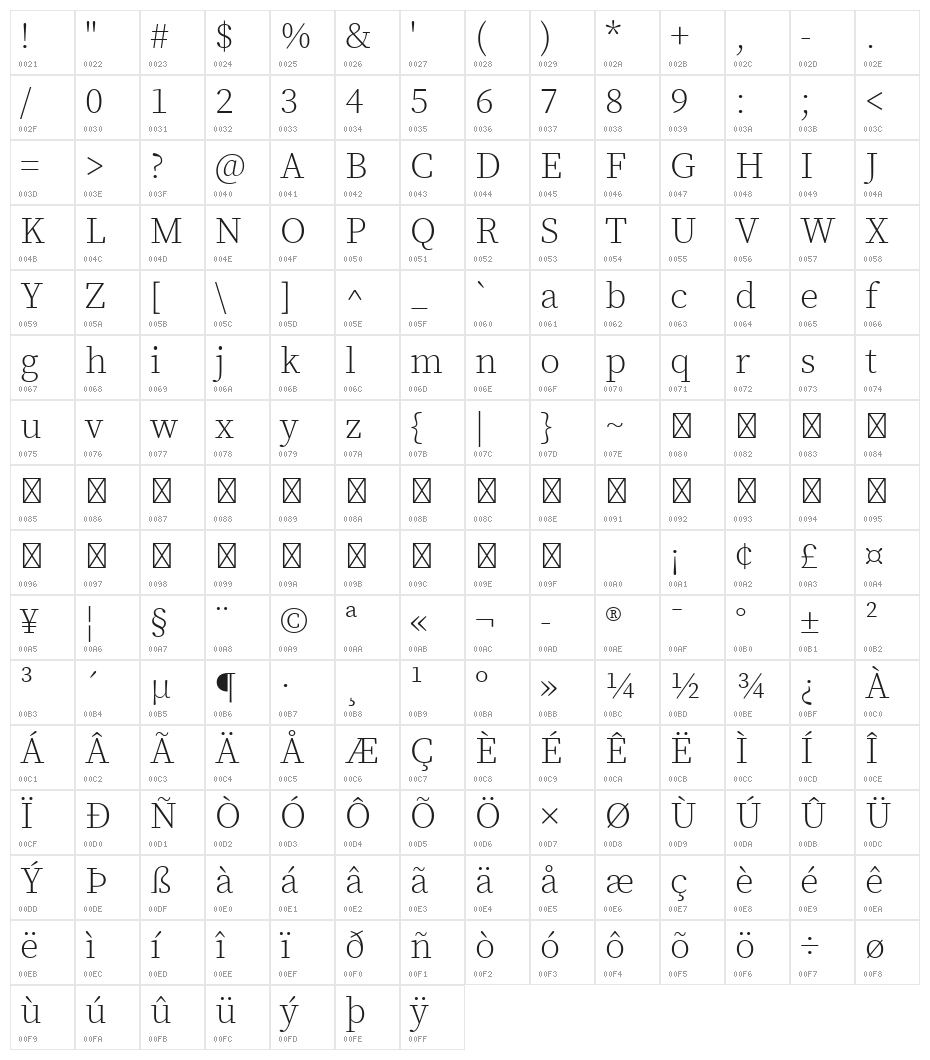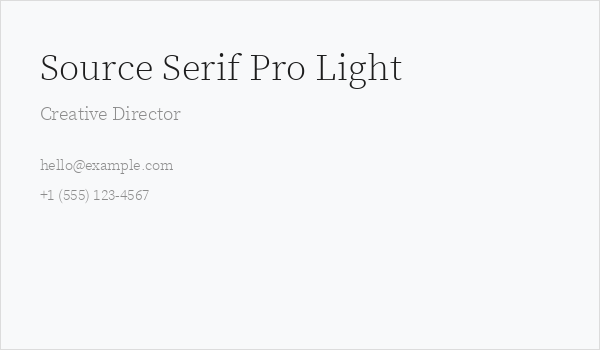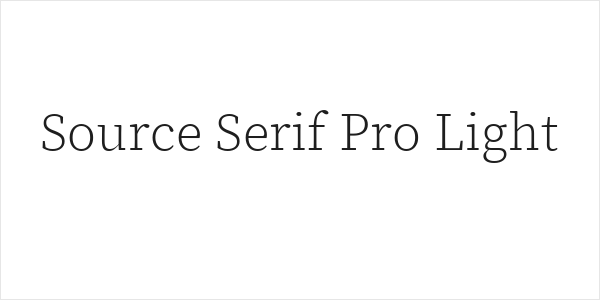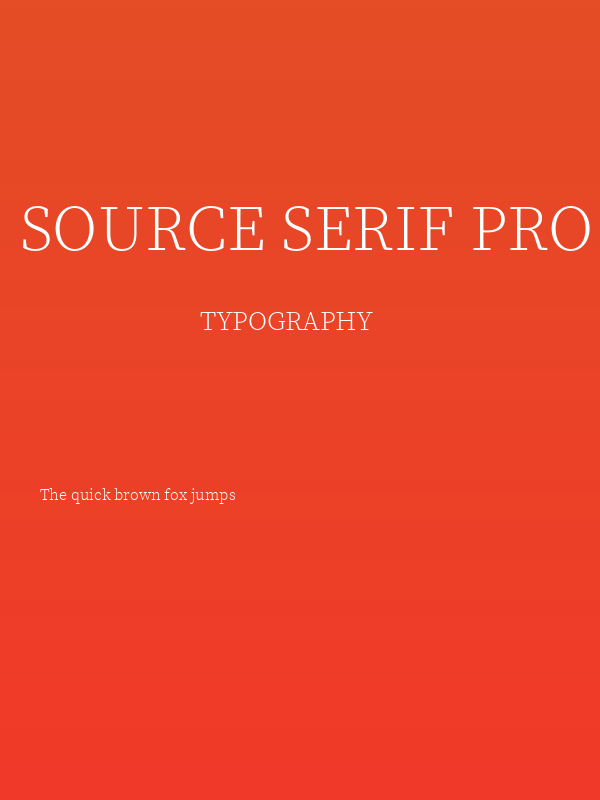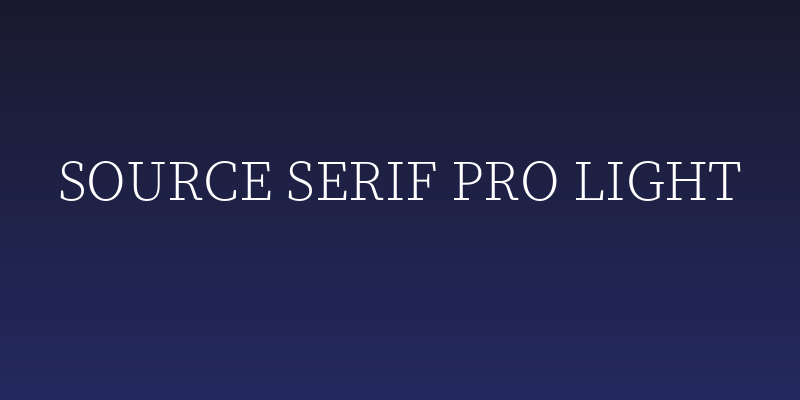
Source Serif Pro Light Font
| Gesamtstil | Classic |
| Anwendungsfall | Body text, Headlines, Editorial design |
| Vorgeschlagene Projekte | Ideal for editorial design, book publishing, formal invitations, and branding projects that require a touch of sophistication. |